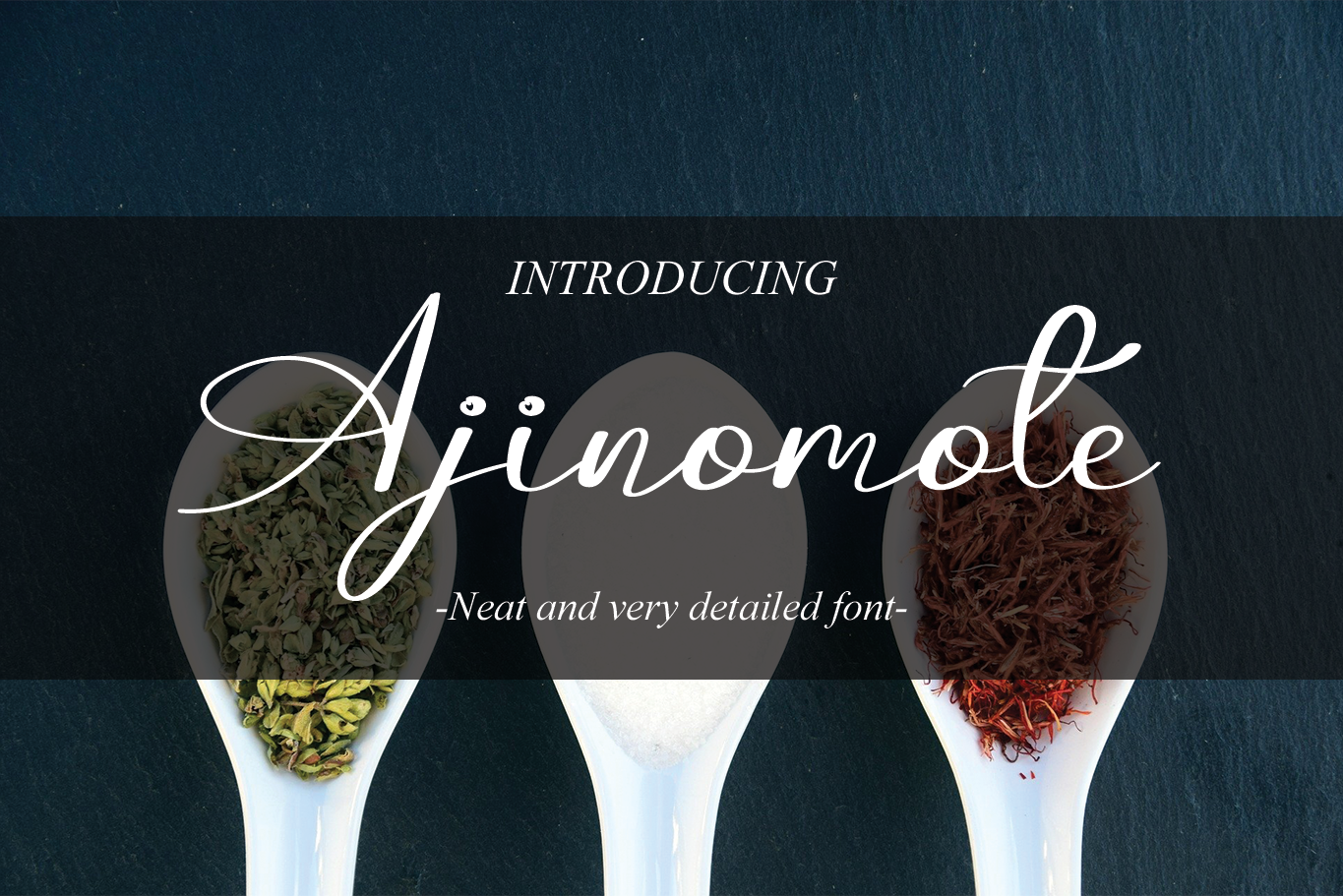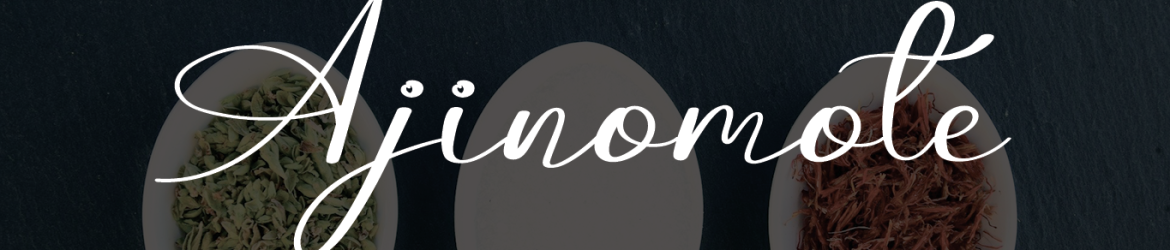
A Jinomote Font é uma elegante fonte escrita a mão que se destaca por suas linhas arredondadas e seu fluxo cívilizatório perfeito para dar um toque especial aos seus projetos digitais. Este tipo de letra não apenas tornará seus textos mais atraentes, mas também adicionará um charme único e autêntico à sua obra. Com o Jinomote Font, criadores de design podem garantir que suas criações se destacam, transformando simples ideias em verdadeiros trabalhos de arte digital. É perfeito para quem busca um toque pessoal e delicado em seu trabalho, seja para o título do seu site ou os subtítulos dos seus vídeos. Uma fonte a ser adotada por qualquer criador de design interessado em criar algo único e autêntico.